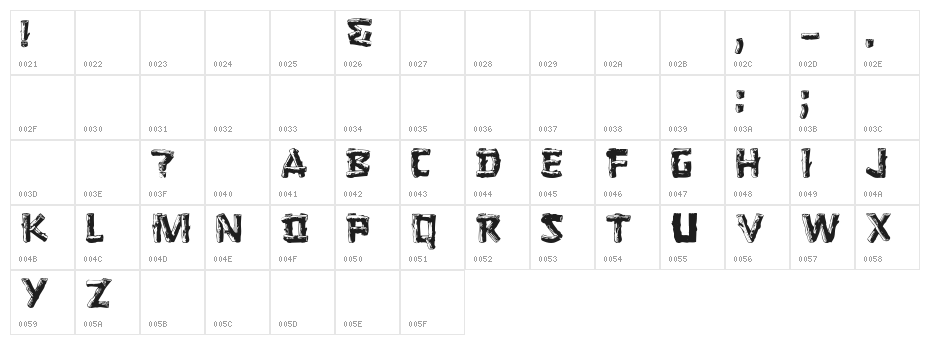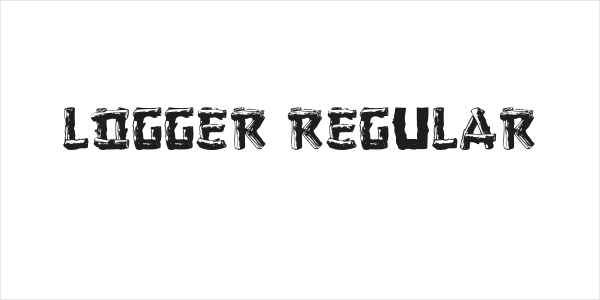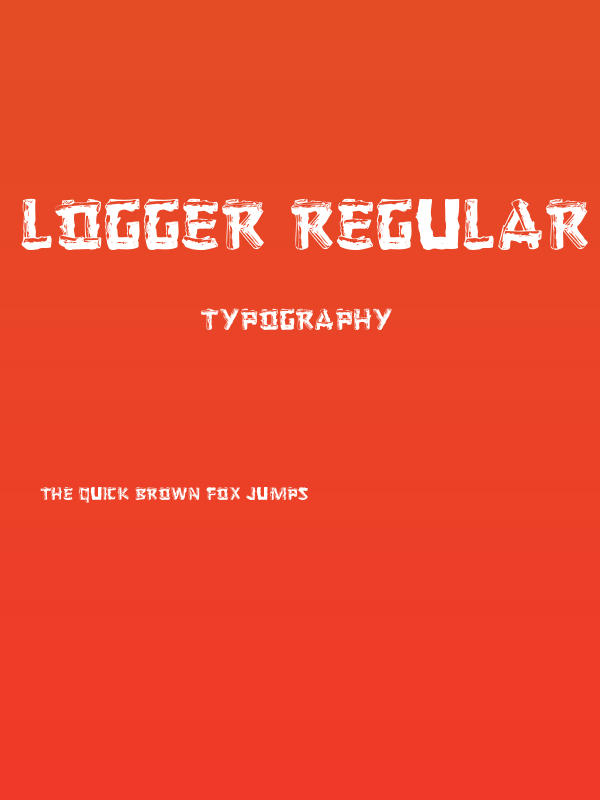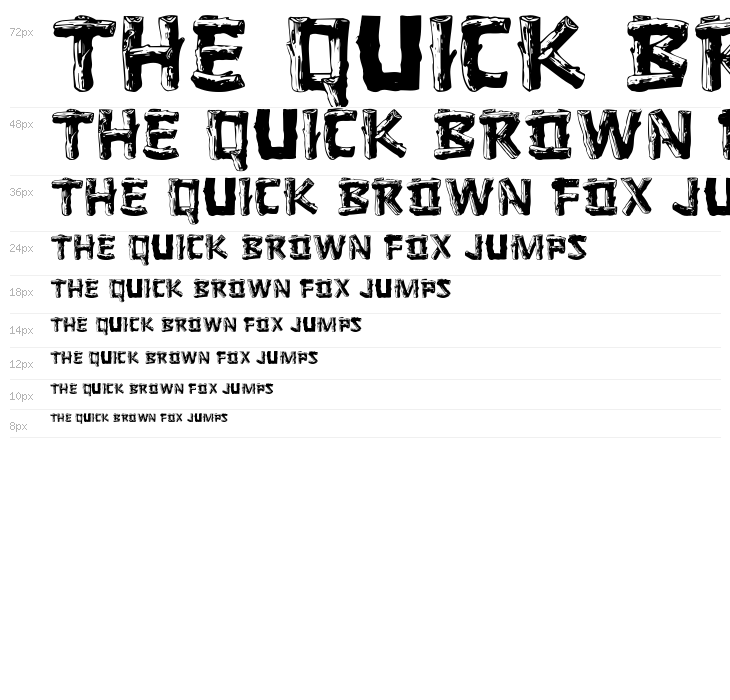
Logger Regular Font
| Stile generale | Rustic, Decorative |
| Progetti proposti | Ideal for outdoor adventure branding, artisanal product packaging, and rustic-themed designs. |